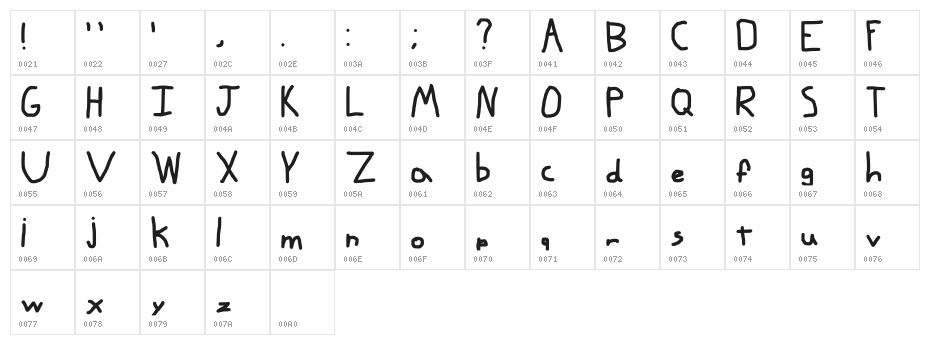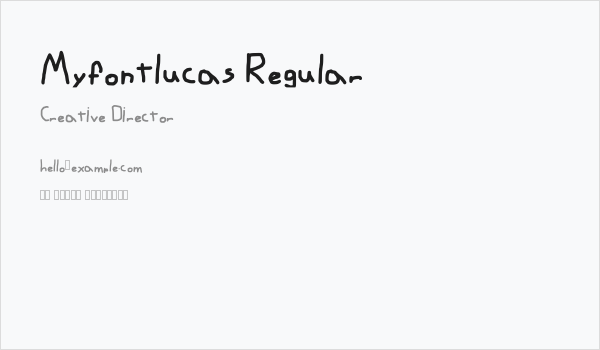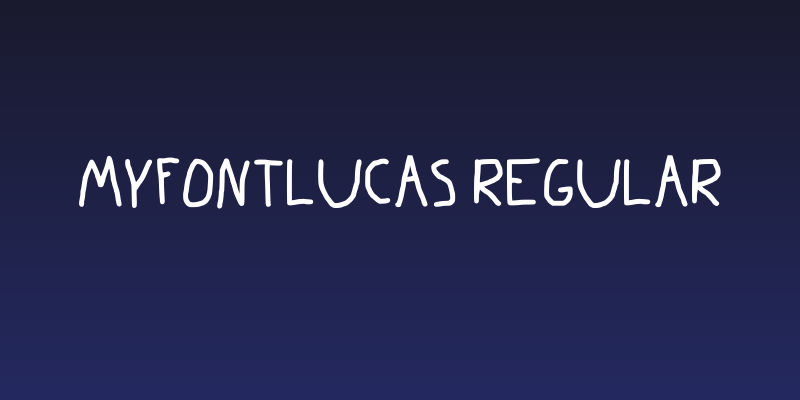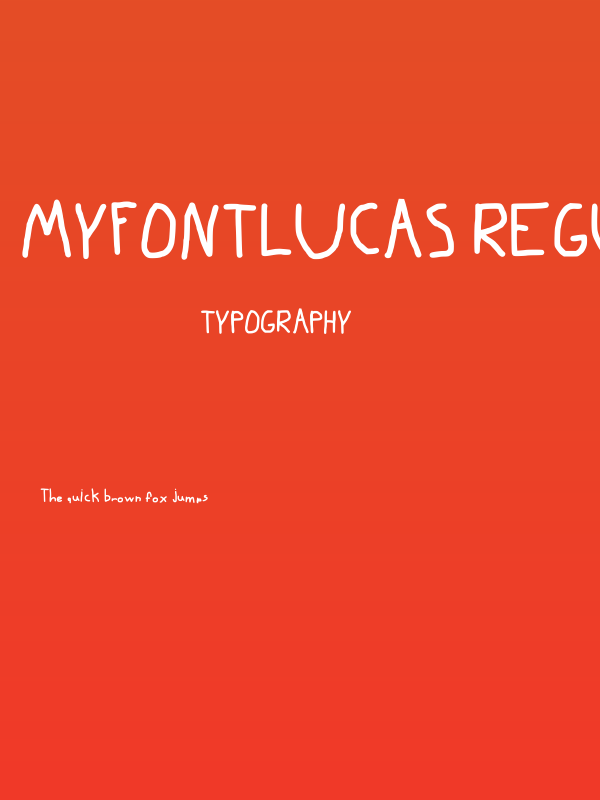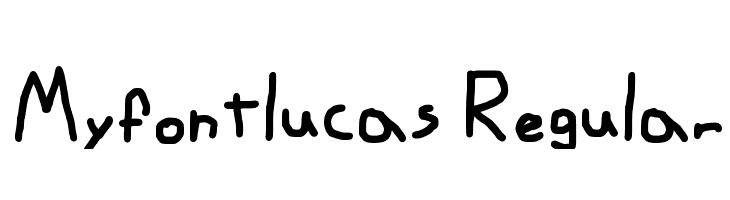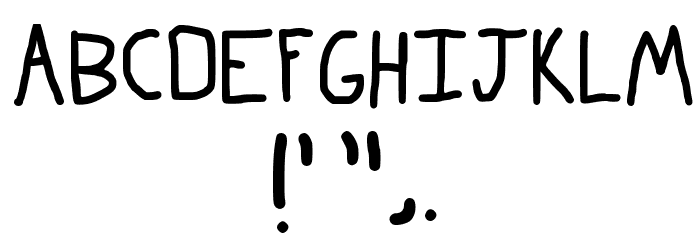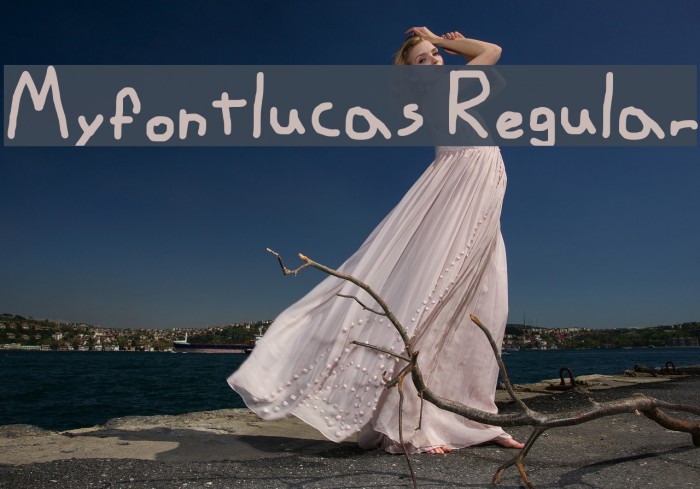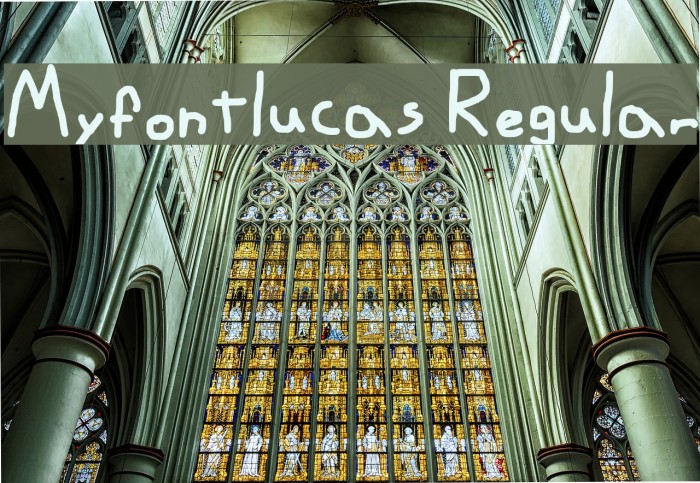
Myfontlucas Regular Font
| Estilo general | Casual, Playful |
| Caso de uso | Headlines, Informal text, Creative projects |
| Proyectos propuestos | Ideal for children's books, greeting cards, personal blogs, and creative branding projects. |